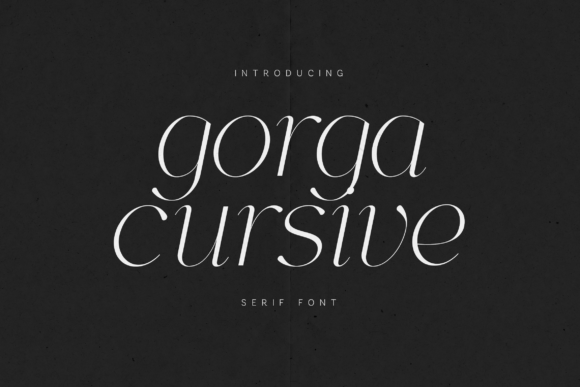
Gorga Cursive
Gorga Cursive์™€ ๊ฐ™์€ ๊ณ ํ’ˆ์งˆ ์ž์‚ฐ์„ ์ฐพ๊ณ  ์žˆ๋‹ค๋ฉด ์ด ํ”„๋ฆฌ๋ฏธ์—„ ํŒจํ‚ค์ง€๋Š” ์ฐฝ์˜์ ์ธ ํ”„๋กœ์ ํŠธ๋ฅผ ์œ„ํ•œ ํ™˜์ƒ์ ์ธ ์„ ํƒ์ž…๋‹ˆ๋‹ค.
POD(์ฃผ๋ฌธํ˜• ์ธ์‡„) ์ œํ’ˆ, ๊ฒฐํ˜ผ์‹ ์ดˆ๋Œ€์žฅ ๋˜๋Š” ์†Œ์…œ ๋ฏธ๋””์–ด ๊ทธ๋ž˜ํ”ฝ์„ ๋งŒ๋“ค ๋•Œ Gorga Cursive๋Š” ์ด์ƒ์ ์ธ ์„ ํƒ์ž…๋‹ˆ๋‹ค.